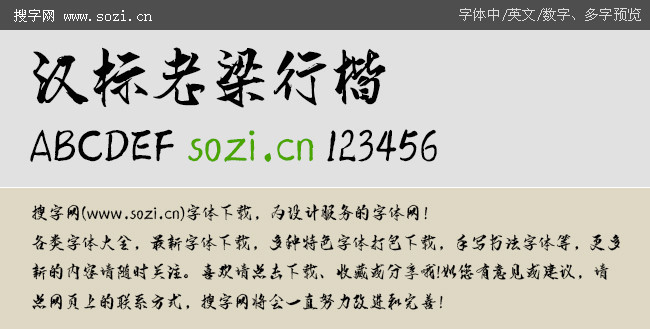
漢標(biāo)老梁行楷
搜字網(wǎng)給大家提供一款漢標(biāo)老梁行楷中文字體下載,漢標(biāo)老梁行楷字體書法氣息濃厚,結(jié)字瀟灑俊逸,運(yùn)筆行云流水,氣韻生動(dòng),充分體現(xiàn)新毛筆行書味道。適用于大標(biāo)題、包裝設(shè)計(jì)、海報(bào)設(shè)計(jì)等應(yīng)用。(本字體為個(gè)人非商用版,如需要商用請(qǐng)聯(lián)系官方購(gòu)買版權(quán))